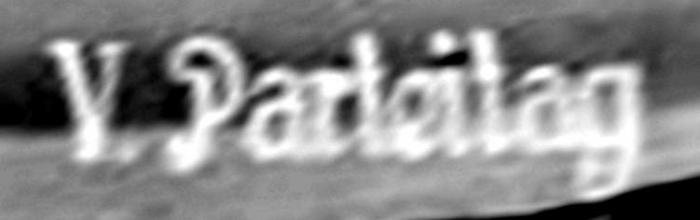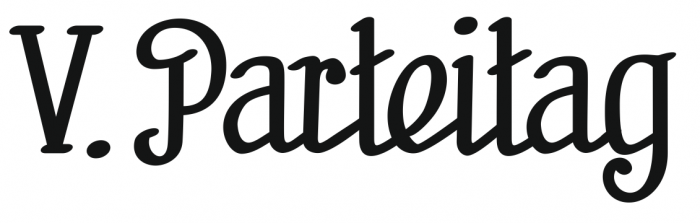
Lok-Schrift gesucht.
Ich suche die passende Schriftart zum Schriftzug "V.Parteitag" auf den Windleitblechen dieser BR 23...
Und wieder einmal ein Fall von Schildermaler! Damals gab es von dieser Zunft noch sehr viele, die dann derartige Beschriftungen völlig frei, wenn auch an Schrifteinmuster angelehnt pinseln konnten. Schau dir hier das hier an:
Gerade in der DDR war diese Zunft noch sehr lange tätig, und das Handwerk noch gut gelehrt.
Mit anderen Worten eine Schriftart in dem Stil gibt es so nicht?
In dem Stil gibt es wahrscheinlich Ähnliches. Aber daß es eine Satzschrift gibt, die dem exakt entspricht und die rechnergängig ist, ist eher unwahrscheinlich. Um genauere Annäherungen zu finden, bräuchte man ein weniger verzerrtes, höher aufgelöstes Bild. Anhand des Photos kann man den Duktus ja nur ungefähr erahnen.
Ich kann das auf dem Bild leider nicht so richtig gut erkennen, aber wäre das hier evtl. so ähnlich?
Ah, jetzt seh ich schon: Das "g" passt schon mal nicht ... schade. Aber vielleicht so was?
Leider trifft es bis jetzt noch nicht ganz ... es muss auch nich unbedingt das gleiche sein nur sollte es schon sehr nah rankommen zumindest was das "V" und das "P" angeht, da diese doch sehr gut sichtbar sind. Leider sind wir Modellbau da etwas Pingelig... Bessere Bilder gibt es leider auch nicht von den Windleitblechen, Sorry.
Hier erst mal schon das, was ich aus dem Foto heraus zerren konnte:
Ich werde mal sehen, was dabei heraus kommt, wenn ich das mal in Corel nachzeichne. Für Modellbahner (und Eisenbahn-Fans im allgemeinen) hab ich ja ein Herz, dafür habe ich ja schon jetzt einiges auf meiner Seite.
Ich werde mal sehen, was dabei heraus kommt, wenn ich das mal in Corel nachzeichne.
so weit meine zeichnerische Interpretation des entzerrten Fotos. Wer weiß, vielleicht mach ich sogar ’nen ganzen Font ’draus?
Für’s erste wird wohl erst mal nur einer ’draus, mit dem sich V. Parteitag schreiben lässt. :-) Mehr, wenn man meint, dass es lohnen täte, auch den Rest der Buchstaben so zu erfinden, was meint Ihr? Und natürlich, passt das in meinen 5 Jahres Plan?
Mir gefällt die Schrift, nur das r sieht irgendwie nach schwerem Seegang aus :)
<kulturbanause>Sieht aus wie eine schlichte Arnold Böcklin ohne jugendstilige Blutgrätsche</kulturbanause>
Mir gefällt die Schrift, nur das r sieht irgendwie nach schwerem Seegang aus :)
Das kommt vom Zug auf den Zug!
@catfonts: